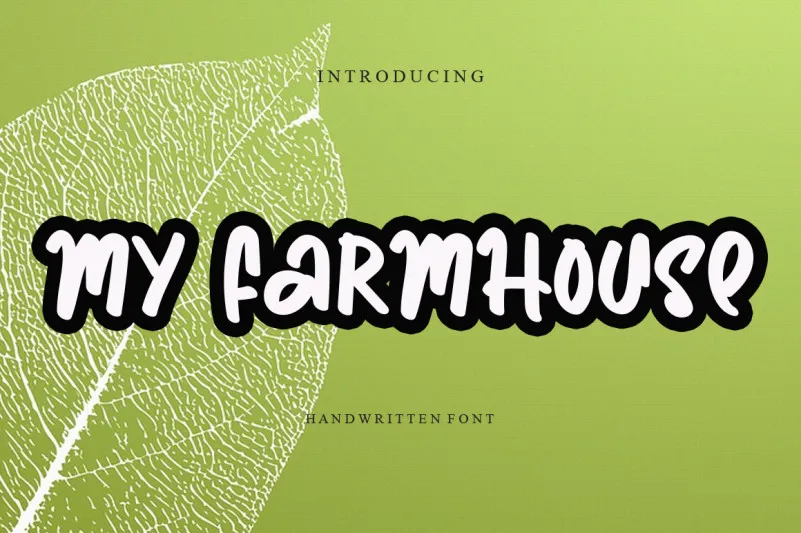
My Farmhouse Font – Download Grátis
A fonte ‘My Farmhouse Font’ foi projetada para ser única, divertida e amigável ao mesmo tempo. Ela é perfeita tanto para uso nas redes sociais como para scripts de escritura manual em um projeto DIY. Este design especializado se destaca entre as muitas opções disponíveis, oferecendo uma fonte versátil que pode transformar a mais simples das ideias criativas em verdadeiros trabalhos de arte. Ideal para decorar publicações nas redes sociais ou adicionar personalidade aos projetos manuais, ‘My Farmhouse Font’ é um recurso indispensável tanto para designers quanto para qualquer pessoa que busque uma maneira única e enriquecedora de expressar sua criatividade.